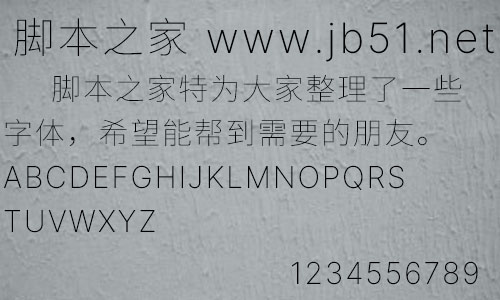
更紗黑體簡(jiǎn)體 SC Extralight 是一款不錯(cuò)的可免費(fèi)商用的藝術(shù)字體,字筆觸較為纖細(xì),字形端正大氣,具有不錯(cuò)的視覺(jué)感,適合應(yīng)用于藝術(shù)設(shè)計(jì)、平面宣傳設(shè)計(jì)、網(wǎng)頁(yè)設(shè)計(jì),書(shū)法字帖等領(lǐng)域,需要的朋友可以前來(lái)本站下載。
更紗黑體(Sarasa Gothic),一款在100%縮放比例下有著優(yōu)秀渲染效果的字體,更紗黑體由Noto Sans / Iosevka和思源黑體的漢字部分合并而來(lái),因此簡(jiǎn)體中文基本不缺字,也有日系漢字的風(fēng)格,并且是開(kāi)源免費(fèi)字體。
更紗黑體與思源黑體對(duì)比,主要是英文部分顯示不同,英文顯示更時(shí)尚。而且增加了斜體。不過(guò)思源黑體具有7字重,而更紗黑體只有5字重,這一點(diǎn)比思源黑體差了一點(diǎn)。